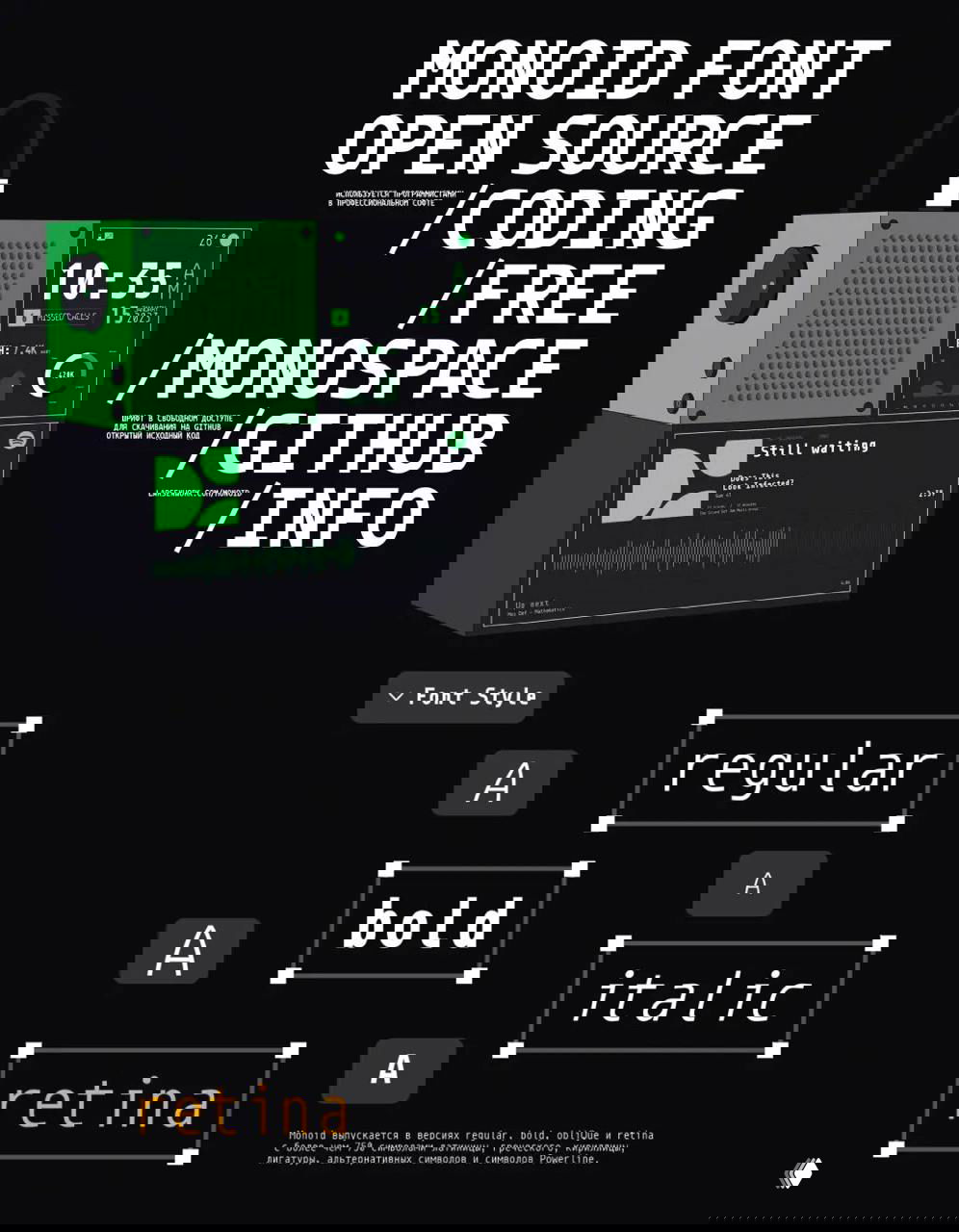
Утилитарный моноширинный шрифт для редакторов кода. Доступны начертания Regular, Bold, Italic и Retina. Оптимизирован для использования на дисплеях с низким разрешениям.